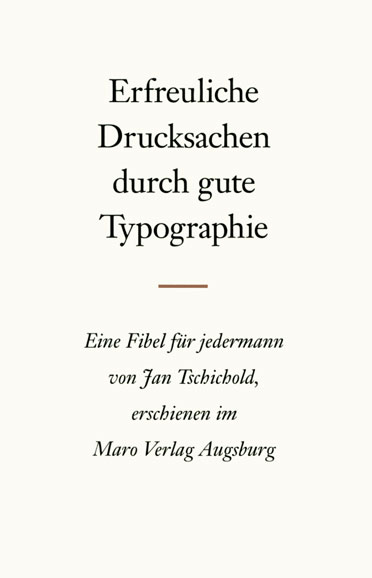
Erfreuliche Drucksachen durch gute Typographie
Eine Fibel für jedermann
Tschichold ist einer der bedeutendsten Gestalter und Schriftschöpfer des letzten Jahrhunderts. Ohne selbst dem Bauhaus angehört zu haben, hat Tschichold die Bauhaus.Typographie theoretisch und mit seinen berühmt gewordenen Arbeiten geprägt wie niemand sonst. Gegen Ende seines Lebens besann er sich auf die Grundlagen der Typographie und schrieb als Handreichung für den Schriftsetzernachwuchs "Erfreuliche Drucksachen durch gute Typographie". Sein Credo: "In einem typographischen Meisterwerk erscheint die Handschrift des Künstlers ausgelöscht".